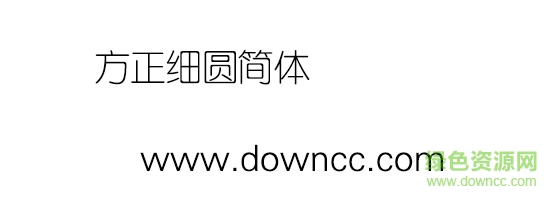
fzy1jw gb1 0是什么字体?fzy1jw gb1 0是一款非常好用的方正细圆简字体软件,字体端正线条流畅,领用领域广泛常用于广告设计、图文印刷、美工制作等多种领域,下载安装即可使用。绿色资源网诚意推荐!
fzy1jw gb1 0字体适用于各种印刷出版物、杂志封面、海报、宣传单,当然更适合网页设计上使用了!